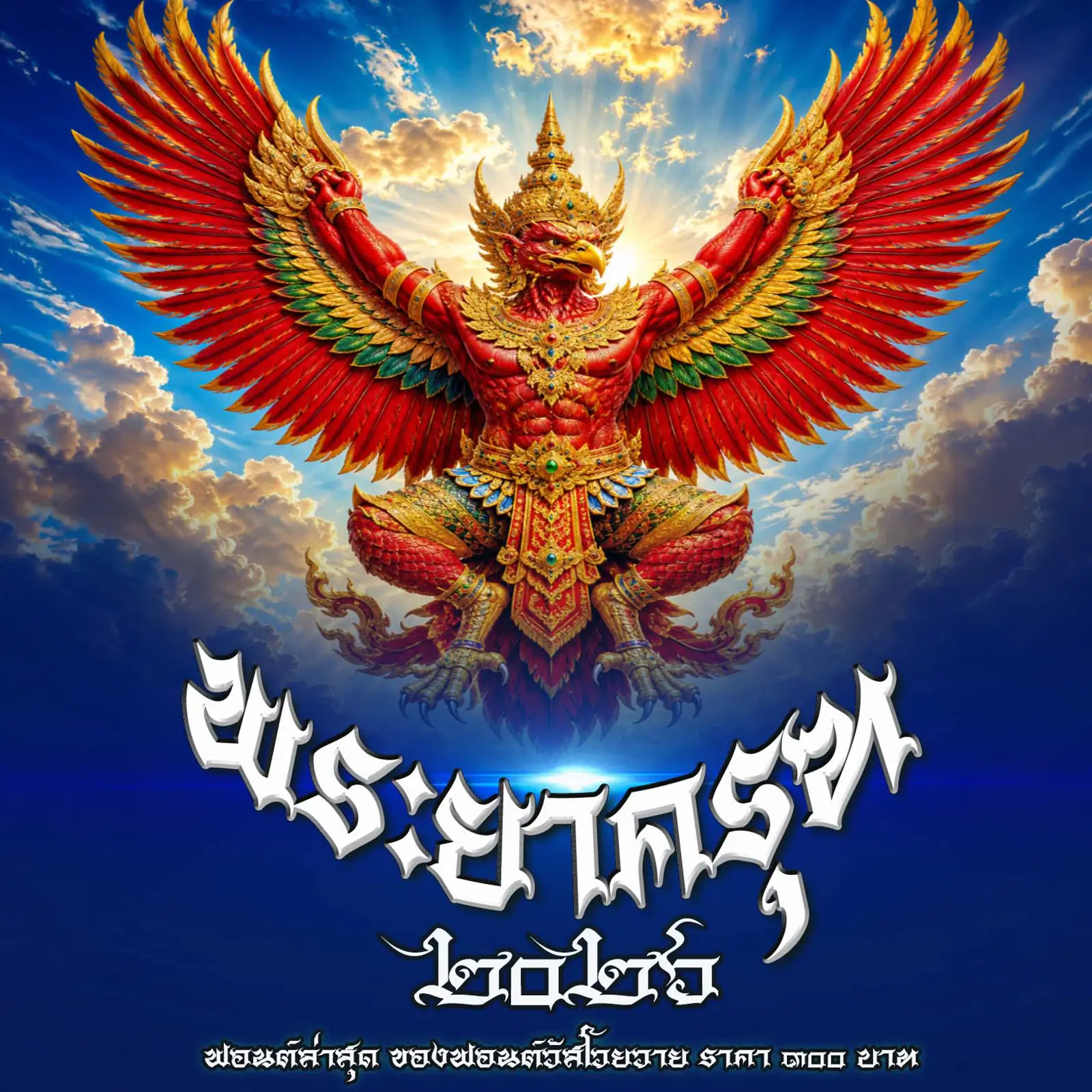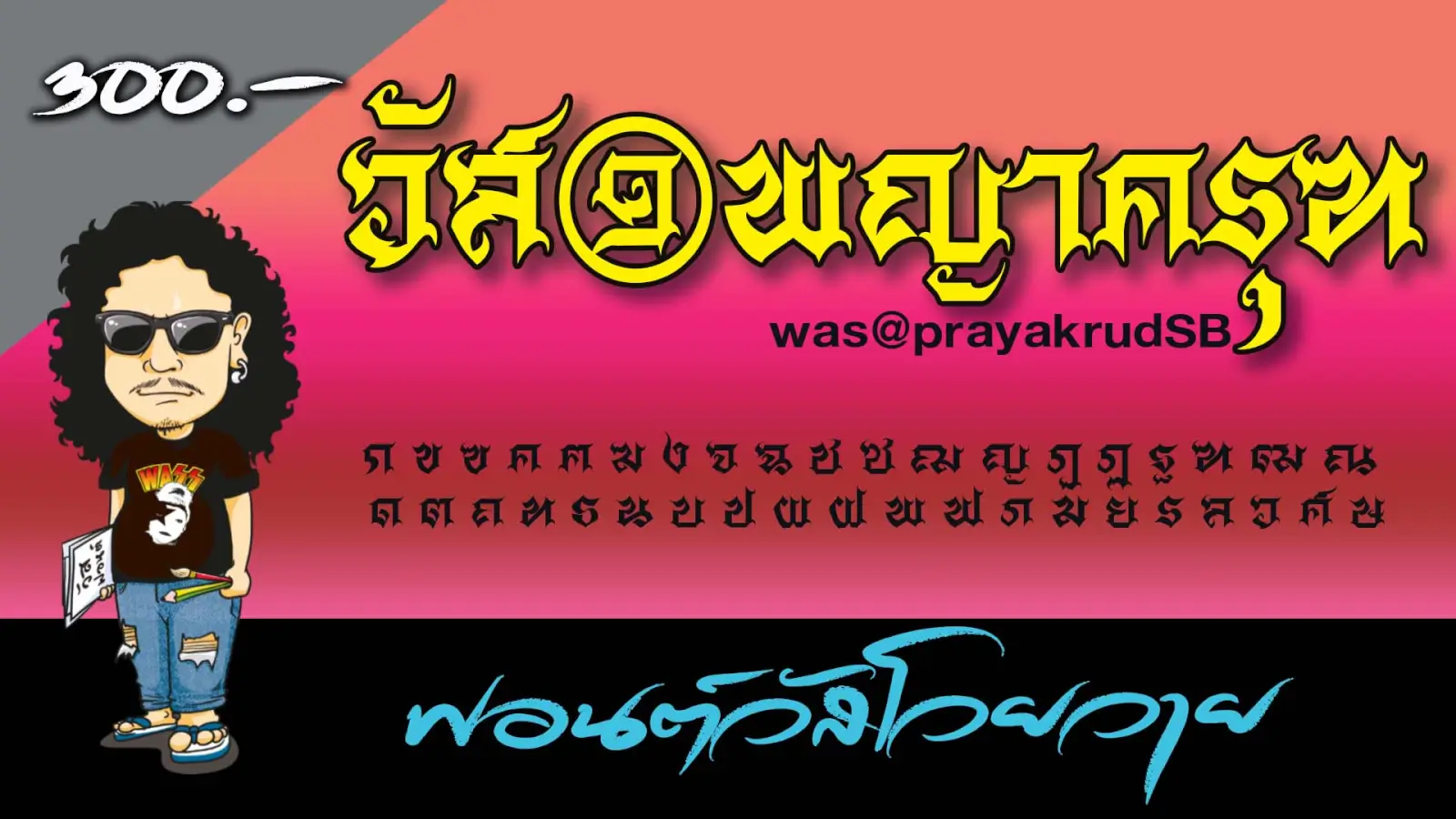
พญาครุฑ (was@phyakrud)
ฟอนต์วัส@พญาครุฑ – ได้รับแรงบันดาลใจจากการเขียนปากกาหัวตัด ซึ่งผมก็จำไม่ได้แล้วว่าเป็นของท่านใด เขียนเลขไทยให้เห็น ๔ ตัว ก็ขอขอบพระคุณมา ณ ที่นี้ ฟอนต์นี้เหมาะสำหรับงานอักษรวิจิตร งานที่ออกแนวไทยๆ และแนวคลาสสิก